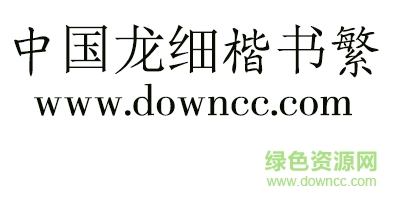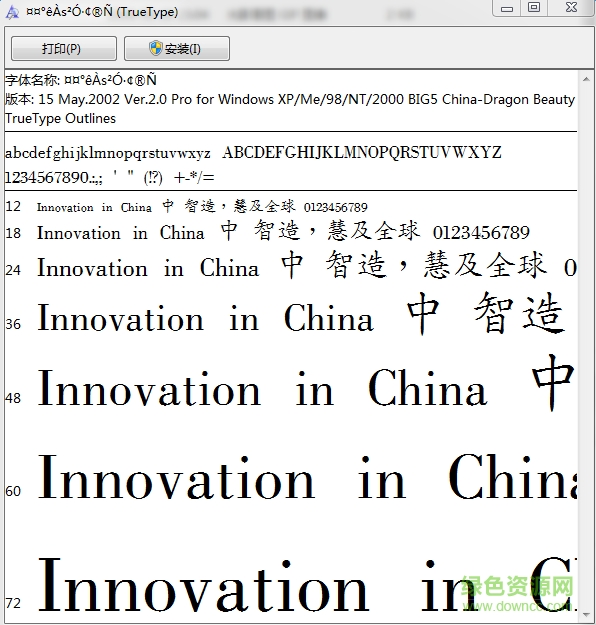
中國龍細(xì)楷書字體是一款比較規(guī)范的楷書體??瑫煮w多用來設(shè)計(jì)廣告、商標(biāo)等。在進(jìn)行書刊排版方面也使用的比較多些!需要中國龍細(xì)楷書體的朋友歡迎下載安裝。
中國龍細(xì)楷書是中國龍字體中的一種,楷書字體向來就使用比較廣泛,不管是用于寫字、創(chuàng)作寫文章,還是書本印刷,都少不了楷書字體,而中國龍細(xì)楷書字體也是很好用,寫出來的字很美觀,有興趣的朋友可以來綠色資源網(wǎng)下載。